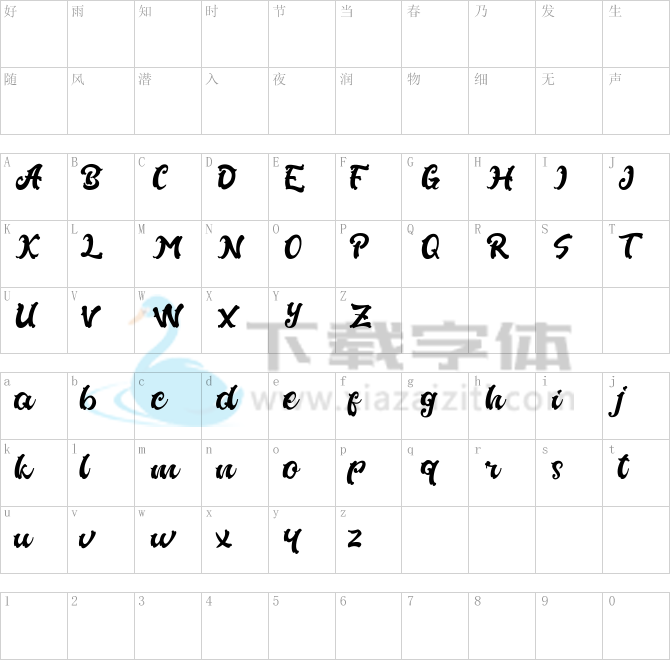
Agasthiya Rococo (Demo Version).ttf字体下载
Agasthiya Rococo (Demo Version).ttf字体下载,这款字体结构工整、笔画清晰,兼顾美观与易读性,适用于标题、正文、海报、包装、LOGO 等多种场景。字形优雅稳定,风格百搭耐看,适配日常排版与创意设计,让文字呈现更舒适、更具质感。Agasthiya Rococo (Demo Version).ttf字体下载一笔一画,皆是细节,以均衡的比例、流畅的线条打造舒适视觉体验,字形端正大气,风格简约现代。无论是商业设计、品牌宣传还是日常排版,都能轻松驾驭,让文字更有格调与力量。Agasthiya Rococo (Demo Version).ttf字体下载字体下载。